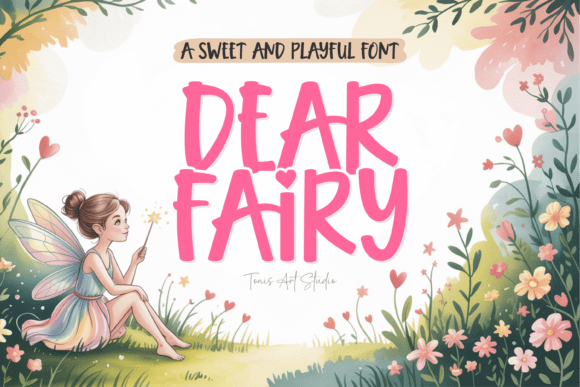
Dear Fairy
إذا كنت تبحث عن أصول عالية الجودة مثل Dear Fairy، فإن هذه الحزمة المميزة هي خيار رائع لمشاريعك الإبداعية.
سواء كنت تقوم بإنشاء منتجات الطباعة عند الطلب أو دعوات الزفاف أو رسومات وسائل التواصل الاجتماعي، فإن Dear Fairy هو الخيار المثالي.